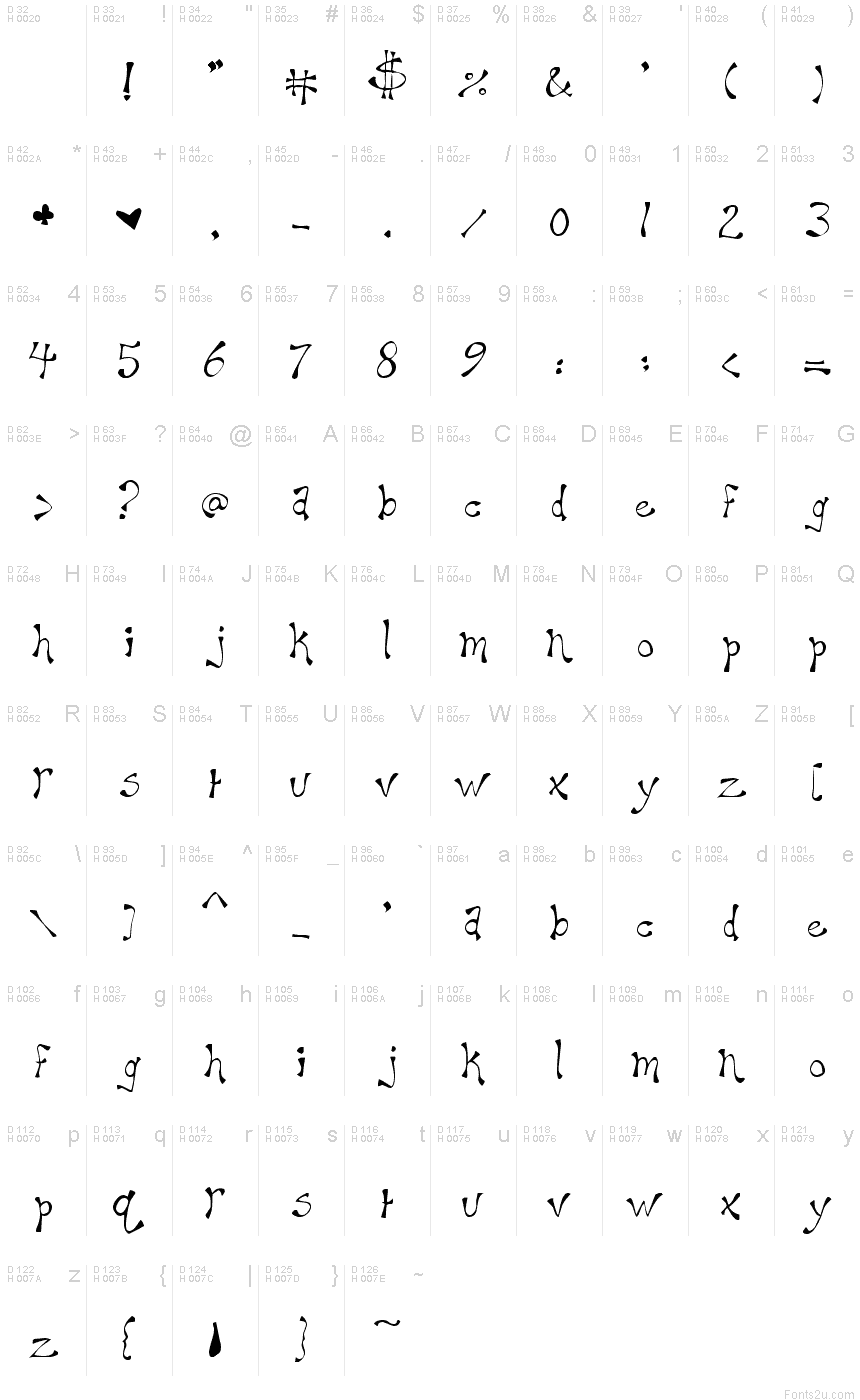
Font Maryellen od Goatee? to darmowy, odręczny krój pisma o luźnym, kaligraficznym charakterze oraz wysokich, wijących się formach, które wznoszą się ponad delikatnie nierówną linię pisma. Litery sprawiają wrażenie szybko nakreślonych piórem, z długimi, płynnymi pociągnięciami, ostrymi łączeniami i otwartymi przestrzeniami, dzięki czemu projekt jest lekki, a nie sztywny.
Maryellen świetnie sprawdza się w zaproszeniach ślubnych, kartkach okolicznościowych, grafikach z cytatami, akcentach w logo i opakowaniach butikowych, ponieważ jej odręczny rytm wydaje się osobisty, a jednocześnie nie wygląda na niechlujny. Ten darmowy font pasuje również do nagłówków w mediach społecznościowych i krótkich tekstów redakcyjnych, gdy potrzebujesz skryptu, który jest nieformalny, pełen wdzięku i wygląda na stworzony ręcznie.